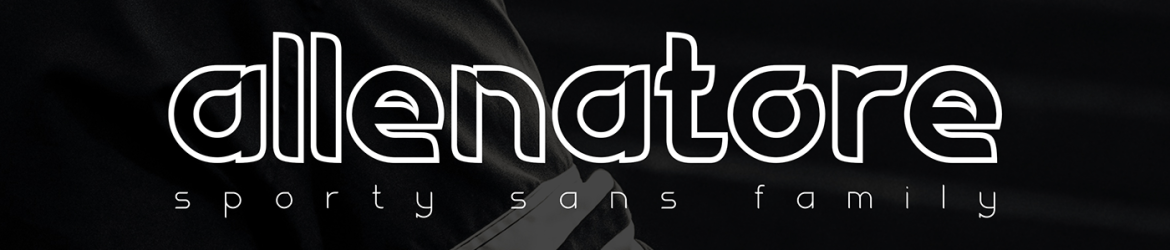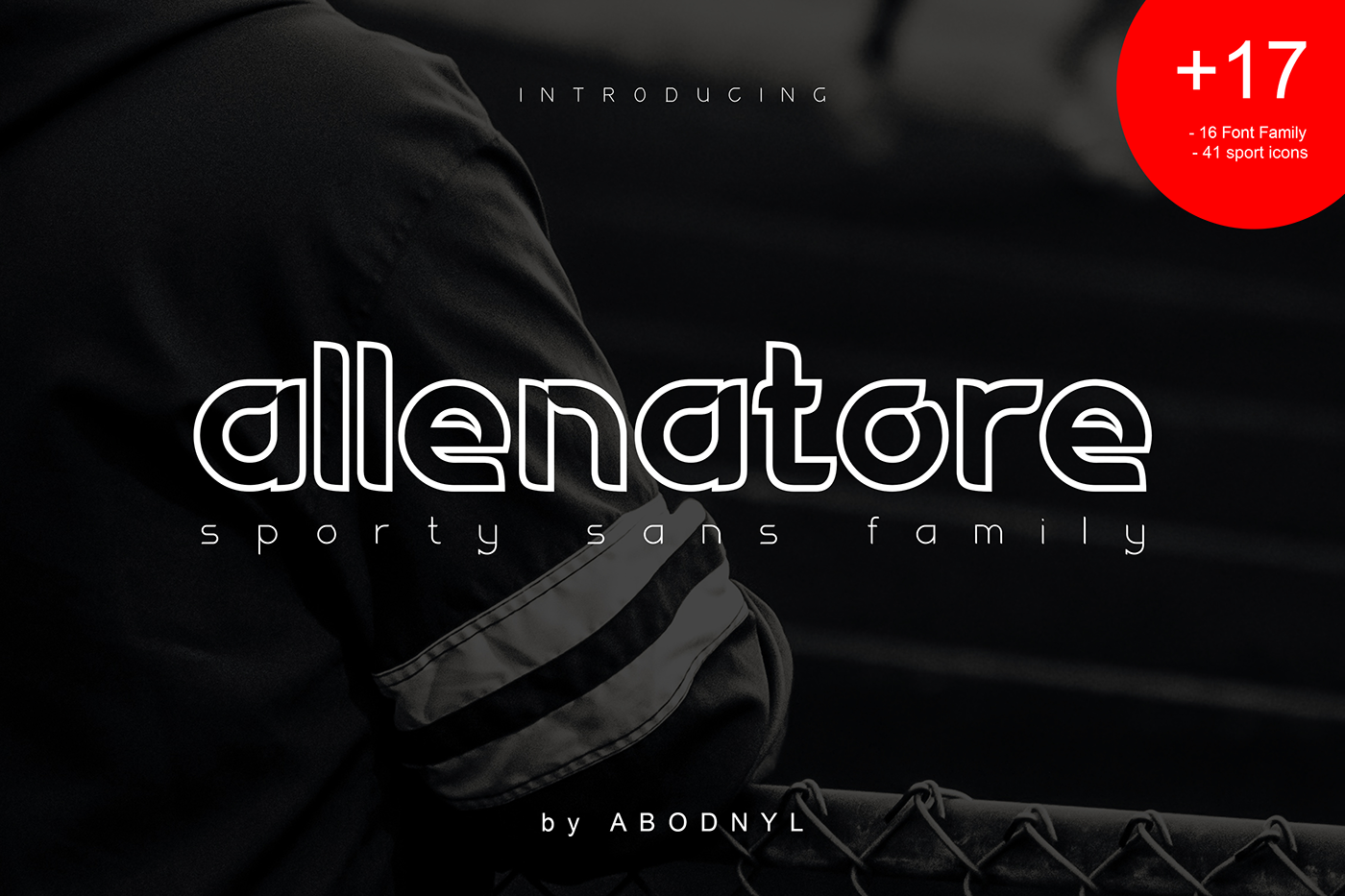
Allenatore Font Family – Fonte Grátis
Allenatore Font Family
Olá! Estamos muito felizes em apresentar a nova família de fontes Allenatore para vocês. Esta criação original é uma verdadeira obra-prima para designers e amantes da criatividade no Brasil e em todo o mundo. Com seu estilo esportivo, a famosa família Allenatore inclui 16 pesos diferentes e 41 ícones esportivos, tornando-o perfeito para uma ampla gama de aplicações. Perfect para logomarcas e branding, headlines, conteúdo de livros, fotografia, convites, marcas d’água, anúncios, papelaria, etiquetas, embalagens de produto – e muito mais! Ele é o verdadeiro encantamento que seus clientes estão esperando. Que tal compartilhar essa fonte incrível com seu co-estudante de design e amigas? Você certamente vai adorar explorá-la.